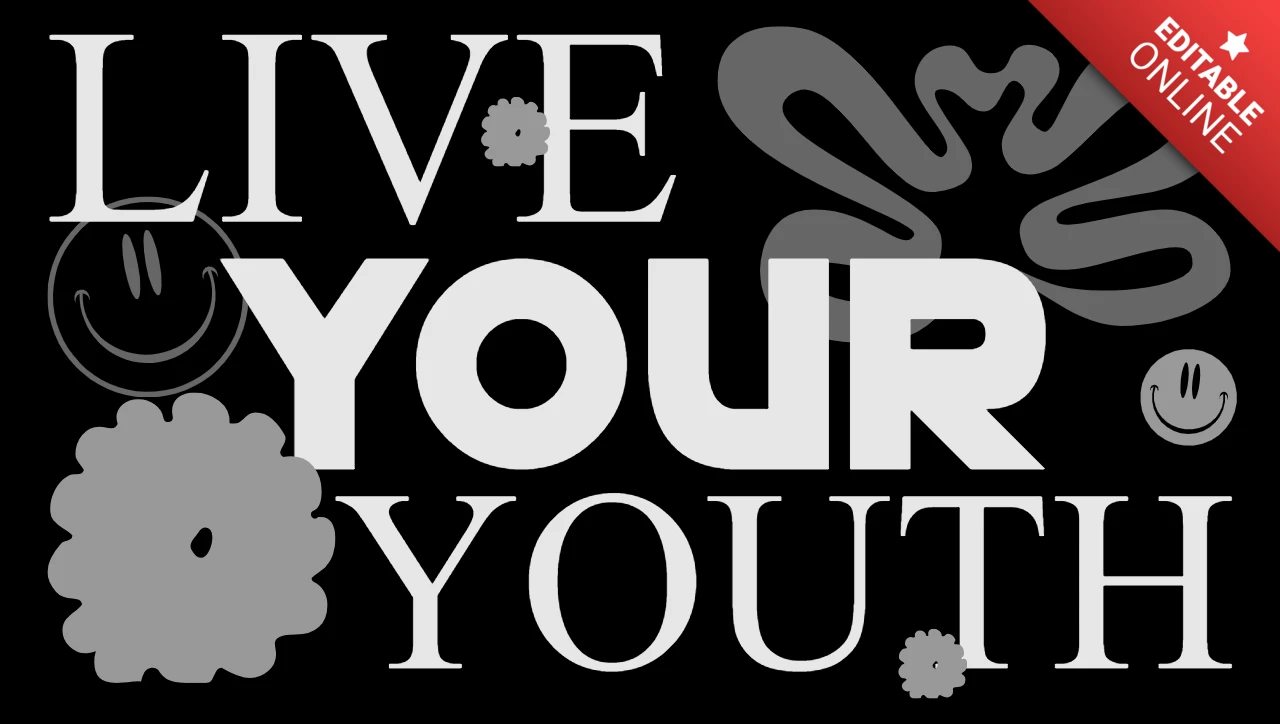
Speelse typografie ontwerp sjabloon voor jeugdige merchandise
Bewerken in Design Studio Downloaden in JPGVerhoog je streetwear merk met onze moderne ontwerpsjabloon, met speelse typografie en levendige bloemenelementen, perfect voor het creëren van opvallende kleding en merchandise die positiviteit inspireert.